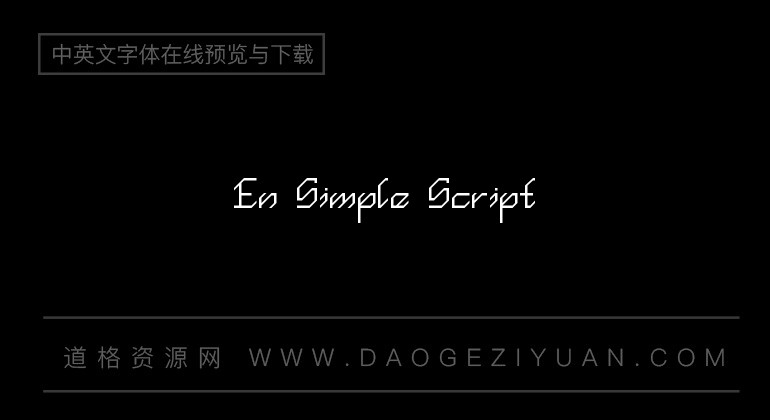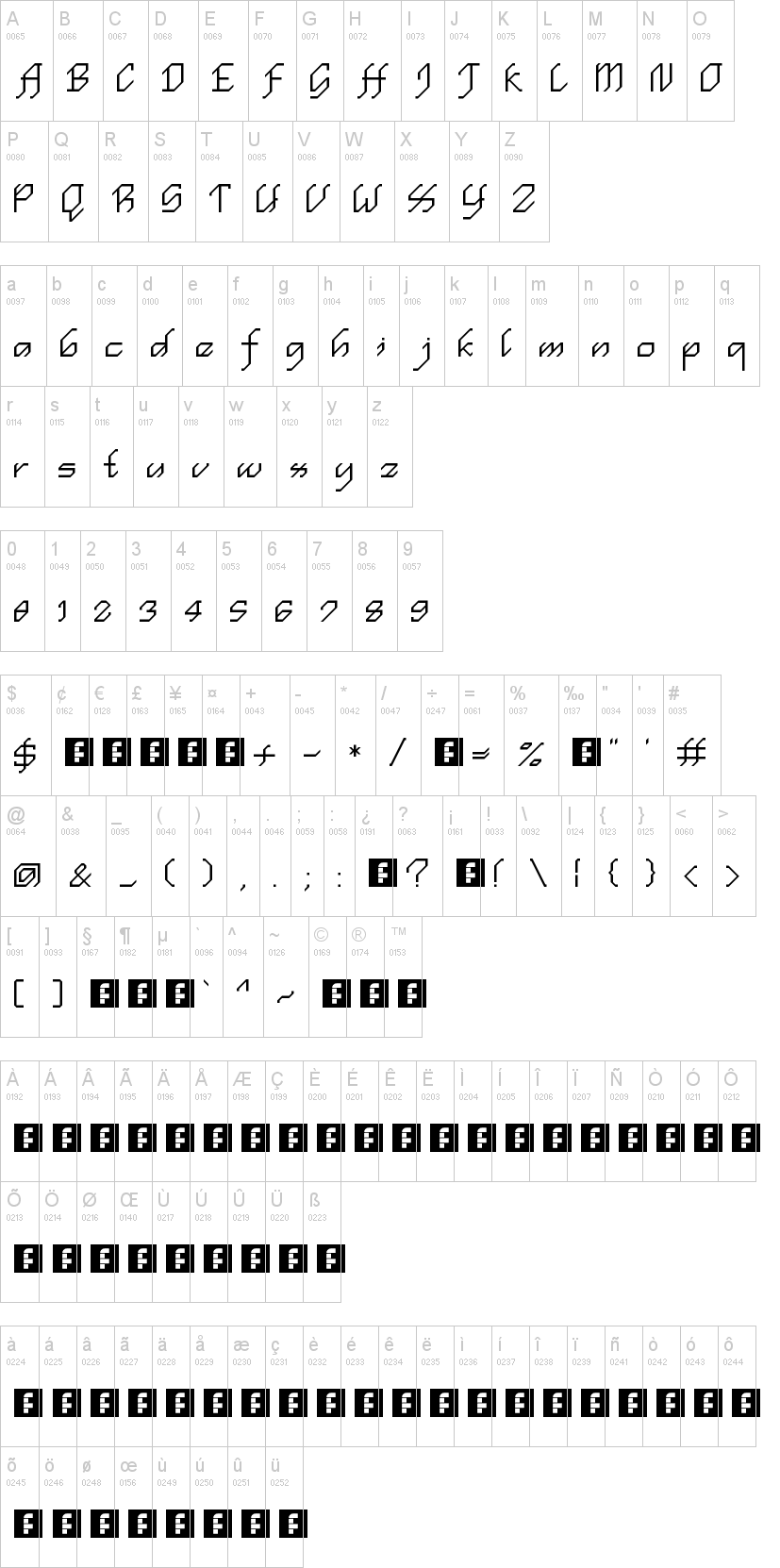
En Simple Script 是一款精致的手写体字体,它拥有细腻的笔画,清晰的线条,流畅的节奏,更具有自然的曲线,以及温暖的氛围。它可以用于各种设计项目,比如海报、卡片、品牌标识、徽标、T恤、婚礼邀请函和名片等等。它的字符也可以用于网页设计,使网页更加有趣,更具有个性化。内容介绍
En Simple Script是一款非常不错的手写艺术字体,具有很好的视觉感,适合于文化类的宣传设计、商业类品牌的广告和产品包装设计以及个性化文字排版等较多场景。